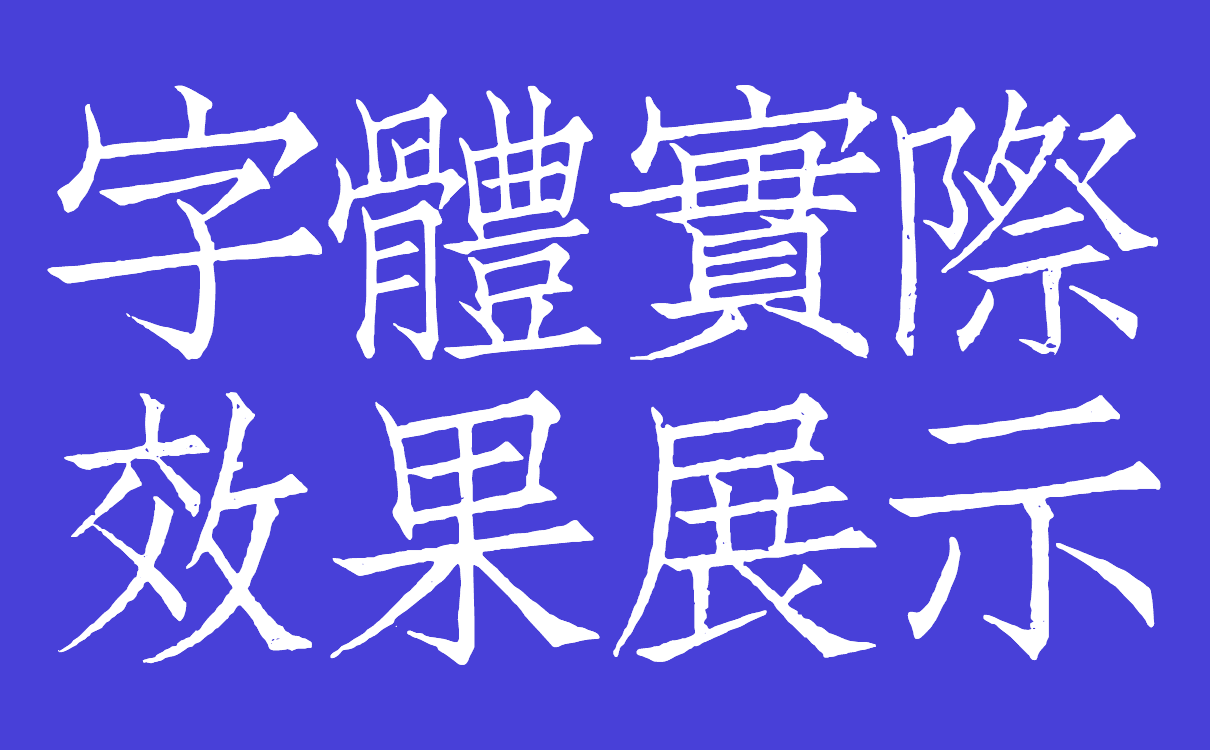
文悦古体仿宋
「文悦古体仿宋」源自中华民国初年的一款活字字体:「聚珍仿宋」。其由丁善之(丁三在)、丁辅之(丁仁)等人创制,他们因不满当时市面上普遍使用的由日本输入的宋体(明朝体)活字字型,故参考刻印史上最为适观的北宋刊本中的字型,设计了这套活字字体。聚珍仿宋是现代仿宋字体的开山之作,风行甚广,采用其排印的中华书局《四部备要》等系列书籍更是造就了出版史上的里程碑。
「文悦古体仿宋」基于聚珍仿宋头号方体字原件制作,除对部分文字作了修缮并增补了一些其不具备的现代常用字外,还专门设计了多项高级特性,以使用户可以方便地利用该计算机字体作出如同古典书籍般的排版效果。